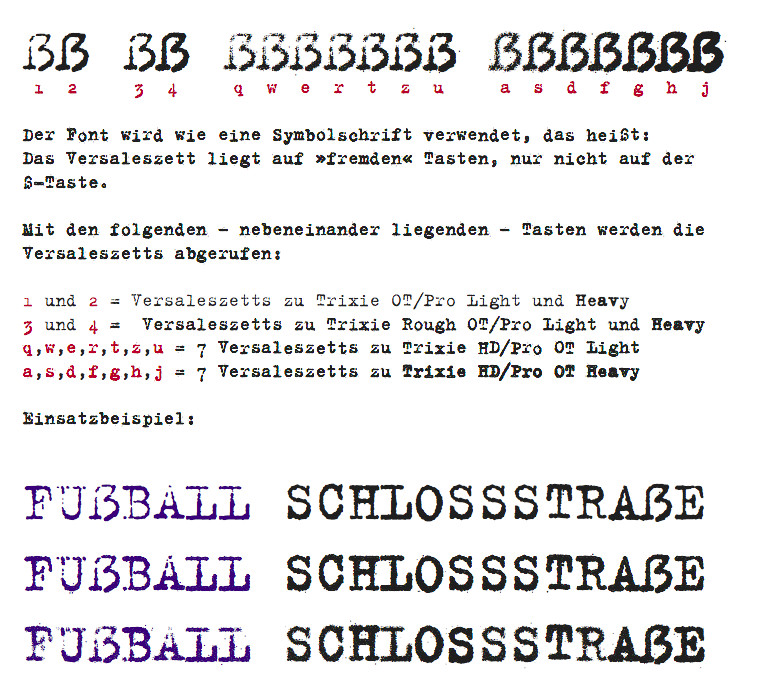
FF Trixie neu aufgelegt
ist das ein Versal-ß…?
ganz schön cool. Wie intensiv die Weiterentwicklungen von solch Klassikern sind.
ist das ein Versal-ß…?
Ja, und es gibt sogar stilistische Versal-ß-Alternativen!
Du meinst, du wolltest der erste mit German-uppercase-double-s-stilistic-alternates sein?
Oh, da hat[te] jemand aber sehr viel Zeit …
Gibt's denn diesmal keinen Schreibmaschinen-Sound dabei?
Was soll das ganze Open-Type-Brimborium wenn das richtige Geräusch beim Tippen fehlt ... :cry:
Du meinst, du wolltest der erste mit German-uppercase-double-s-stilistic-alternates sein?
Weiterlesend musste ich feststellen dass etwas anderes gemeint war (nämlich die 7 Varianten für Schreibmaschinen-Look).
Ich überlege mir, wenn für die jeweilige Schrift passend, runde und eckige Versal-ß und eventuell auch eins mit Unterlänge mit anzubieten, um es dem interessierten Anwender leichter zu machen, die für ihn stimmigste Form zu wählen. Da sich die Frage nach der "perfekten" Form sich nur langsam klärt: warum nicht vorläufig alle zur Verfügung stellen. Andererseits weicht das dann wieder Konventionen auf und wird noch länger nicht festgelegt...
Aber: anderes Thema. :tutor:
Hier Trixie.
Die Form ist immer gleich, nur eben passend zu den einzelnen Trixie-Schnitten:
Stimmt. Mir war aber so, als waren tatsächlich Versal-ß-Alternates geplant. Aber ist ja auch egal. Ich finde die Trixie HD erste Sahne. Diese ganzen OT-Features werten die gute alte Trixie nochmal richtig auf. Ich finds Klasse, wenn die Foundries die Möglichkeiten beim Ausbau in das Format auf diese Art nutzen.